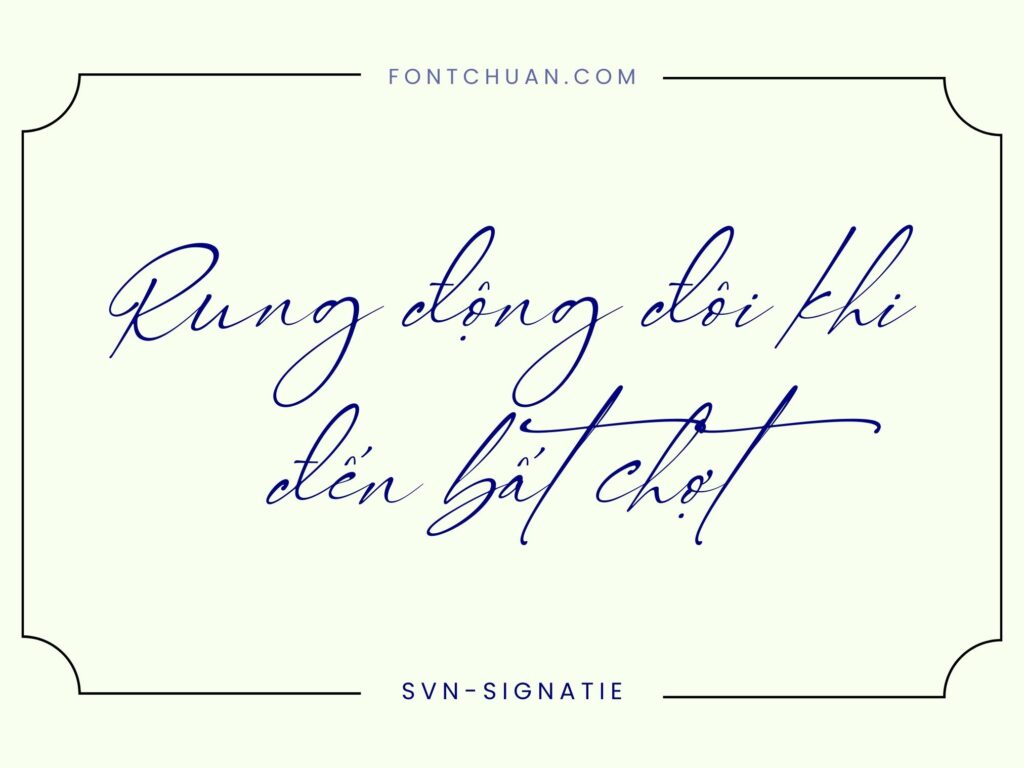
Font SVN Signatie Việt Hóa
Font SVN Signatie là phiên bản Việt hóa của kiểu chữ Signatie, được thực hiện bởi STYLEno.1 Fonts. Signatie là một font chữ ký phong cách viết tay tinh tế, được thiết kế bởi BrandSemut. Font này được xây dựng với các tính năng OpenType, bao gồm ligatures và các nét kết thúc, cùng với các ký tự số, dấu câu và hỗ trợ đa ngôn ngữ. Với kết cấu mượt mà, Signatie phù hợp cho nhiều kỹ thuật in ấn khác nhau như thêu, cắt laser, cricut, ép kim, v.v. Font này lý tưởng cho các thiết kế logo, tiêu đề, bao bì sản phẩm và các ấn phẩm truyền thông. ([STYLEno.1 Fonts](https://www.svnfont.com/viet-hoa-svn-signatie/))
SVN Signatie phù hợp cho các dự án thiết kế yêu cầu sự thanh lịch và chuyên nghiệp, như thiết kế logo, tiêu đề, bao bì sản phẩm và các ấn phẩm truyền thông. Các ngành nghề như thiệp cưới, giáo dục và bất động sản có thể tận dụng font này để tạo điểm nhấn trong thiết kế. Ngoài ra, font cũng thích hợp cho các sự kiện như Tết, Valentine, Sinh nhật và các lễ hội khác.